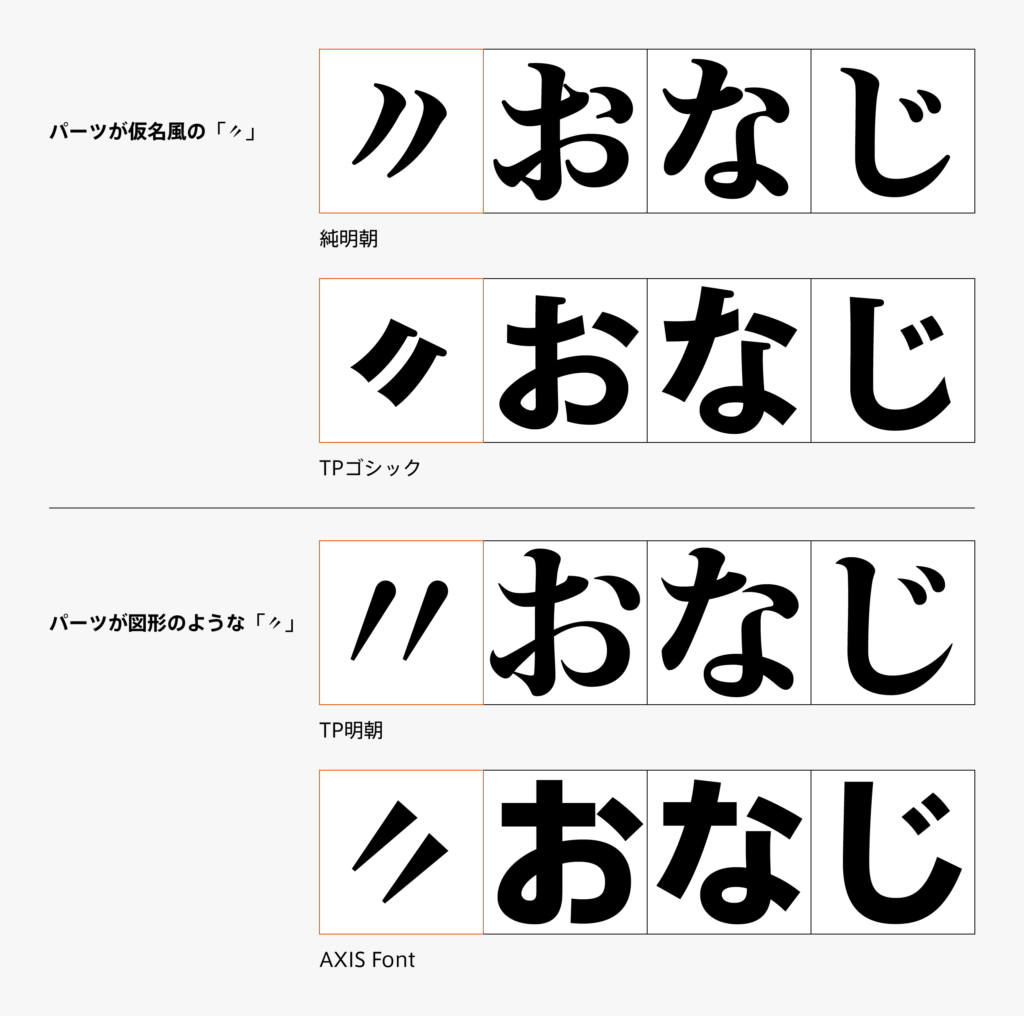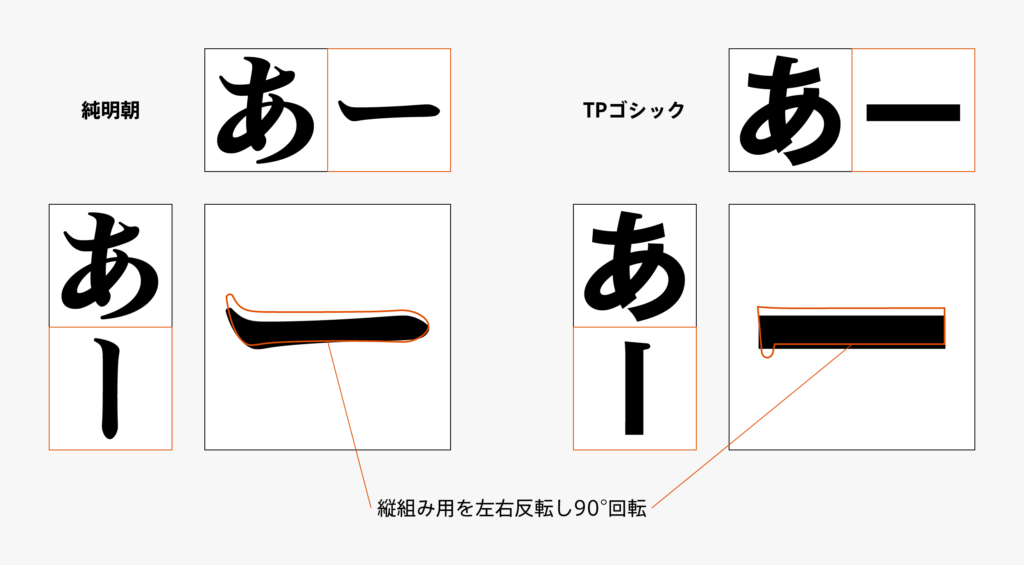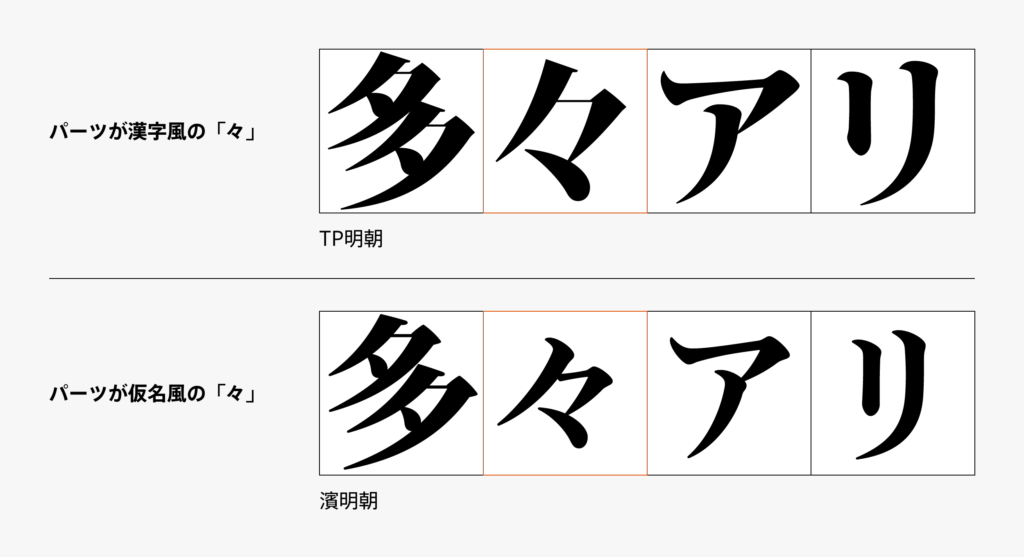
和文約物02「音引き・踊り字」
今回扱うのは音引きと踊り字です。
音引き(ー)はシンプルな一本の線のようでいて、やはり各フォントに合わせてデザインする必要があります。縦組み用と横組み用の作り分けもあり、ただ回転させるのではなく起筆終筆の形を変えたり線の角度を調整したり同じくらいの太さに見えるように細かな調整を加えたりしています。音引きの制作は仮名のデザインが決まった後にしたいと思うこともあるのですが、カタカナの制作中に単語を組もうとすると長音を含むものが多いため早々に音引きが欲しくなります。
踊り字は「ゝ々〃」など同じ文字の繰り返しを表す約物の総称です。「ゝ」は一の字点、「々」はノマ点、というようにそれぞれの呼称もあります。「々」を明朝体で見ていると、パーツが漢字風のものと仮名風のもので2種類があることがわかります。
同じくデザインが分かれる踊り字としてノノ字点「〃」があります。パーツが仮名風のものと図形のようなものの2種類で、こちらはサンセリフ体・ゴシック体のフォントでも違いが見て取れます。